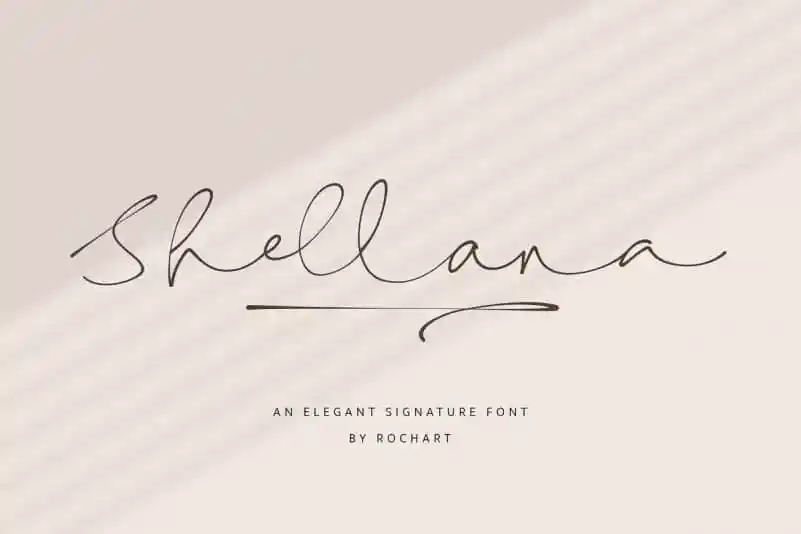
Shellana Script Font – Download Grátis
Shellana Script é uma fonte elegante e viva criada para deslizar letras com fluidez e graça. Esta fonte contém caracteres maiúsculos e minúsculos, números romanos, um grande número de pontuações, suporta múltiplas línguas internacionais, ligaduras, alternativas estilizadas e “swashes”. Suas letras se movem com uma liberdade contagiante, tornando-a ideal para criar design gráfico arrojado, como headlines de sites ou publicações de revistas. Esta fonte traz um toque moderno ao seu trabalho, mas mantém o encanto clássico que tanto se prega na tipografia script. Para quem busca uma fonte que transmite a essência da criatividade e do design contemporâneo, Shellana Script é o ideal escolhido.